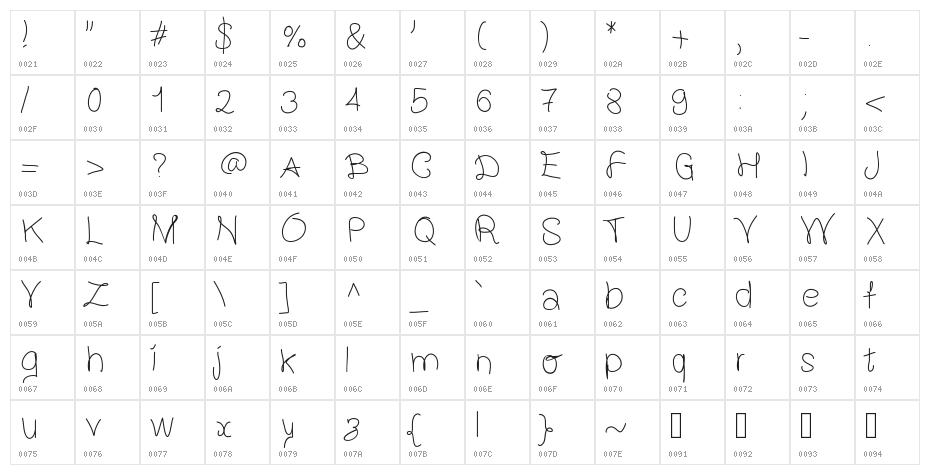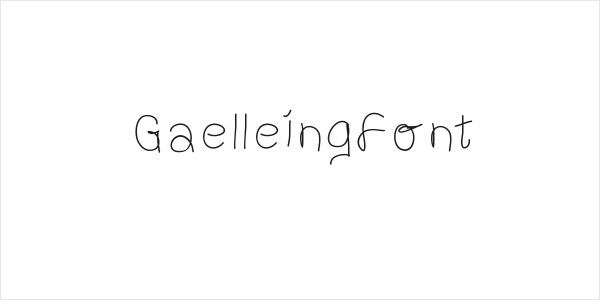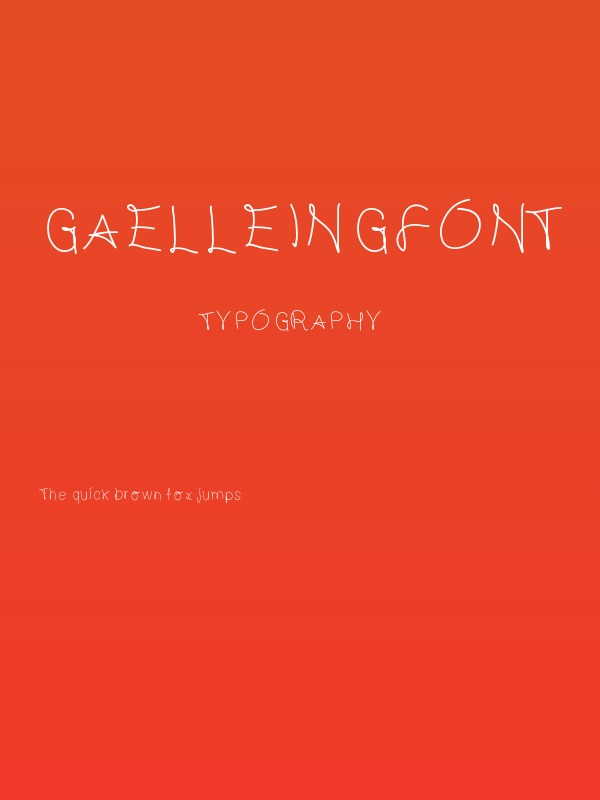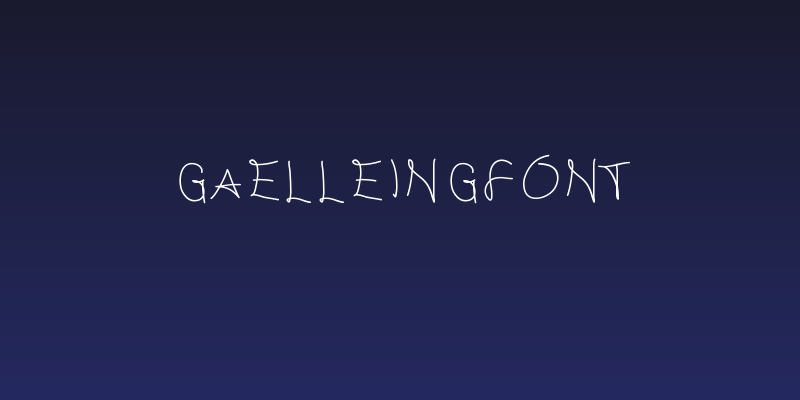
GaelleingFont Font
Gaelleing
| Caso d'uso | Headlines, Logos, Creative projects |
| Progetti proposti | Ideal for children's books, greeting cards, playful branding, and creative invitations. |